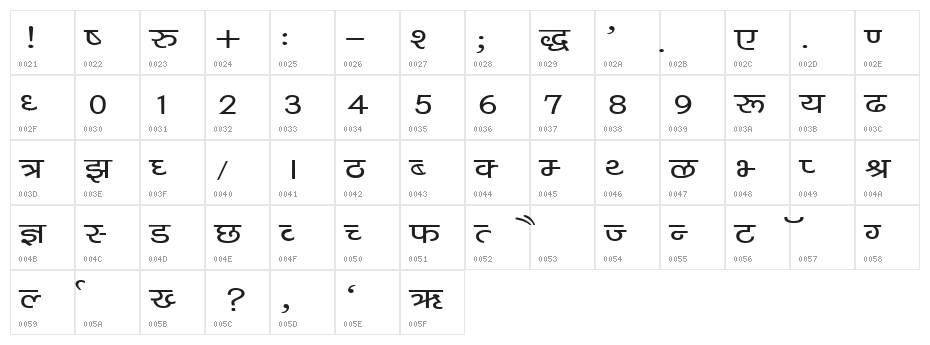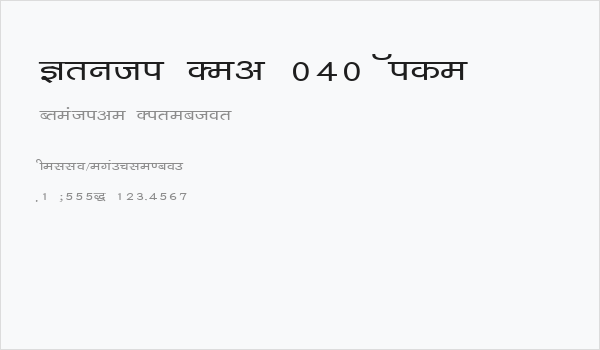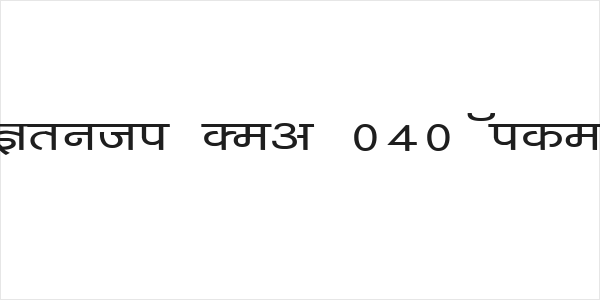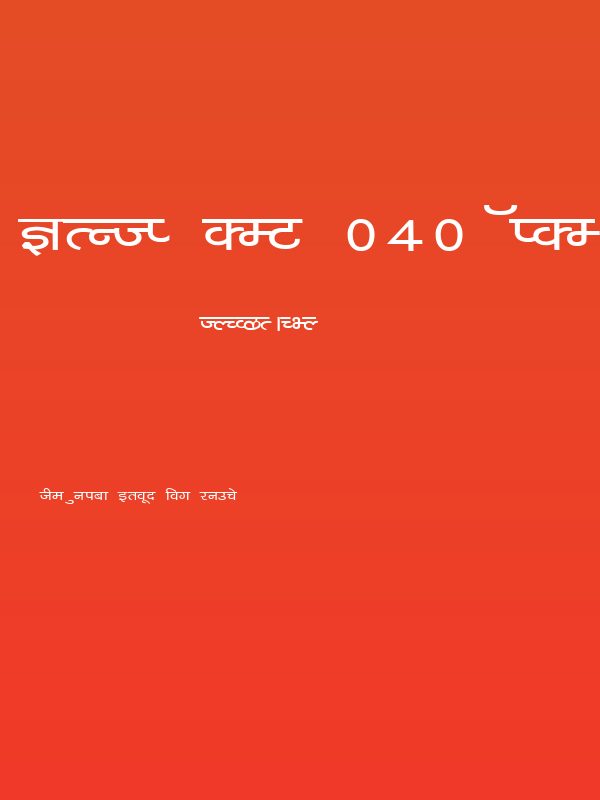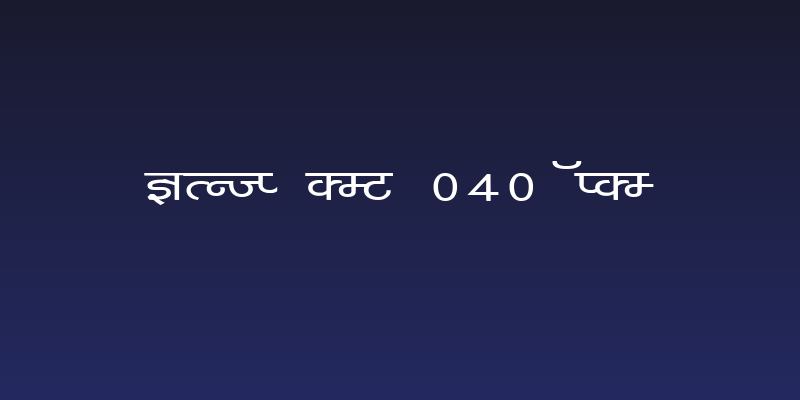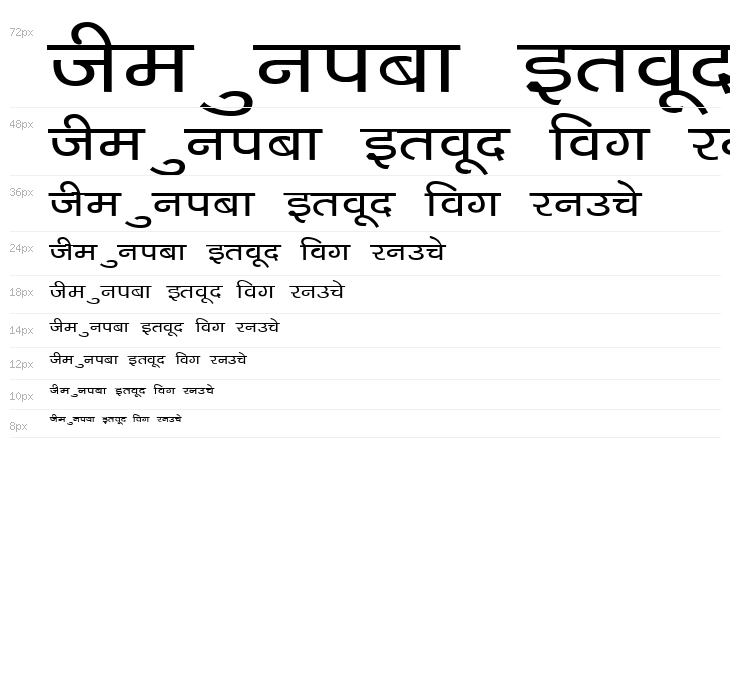
Kruti Dev 040 Wide Font
✎ Script
| Ширина | Expanded |
| Область применения | Headlines, Signage, Educational materials |
| Рекомендуемые проекты | Ideal for signage, posters, educational materials, and digital content requiring Devanagari script. |